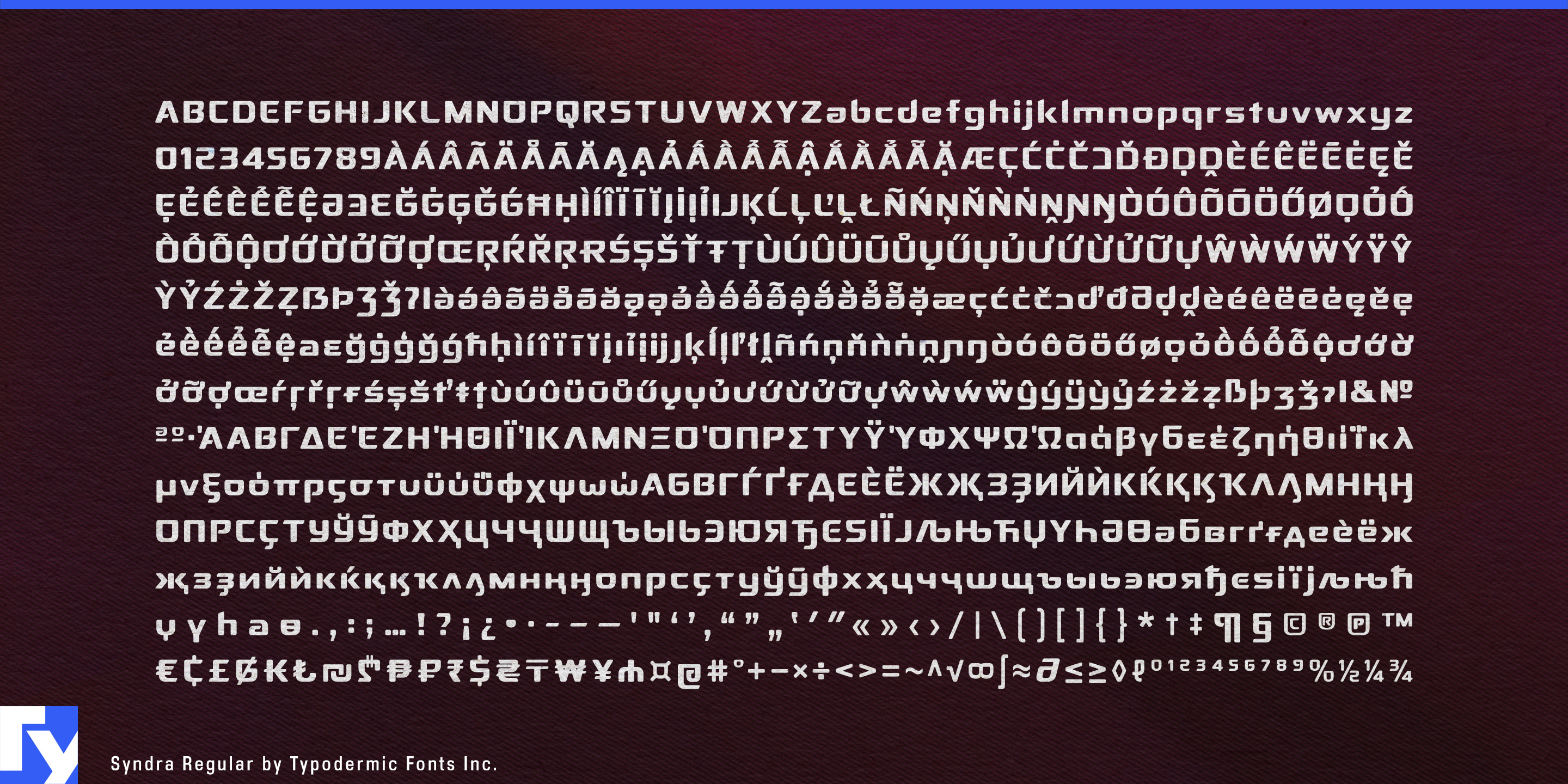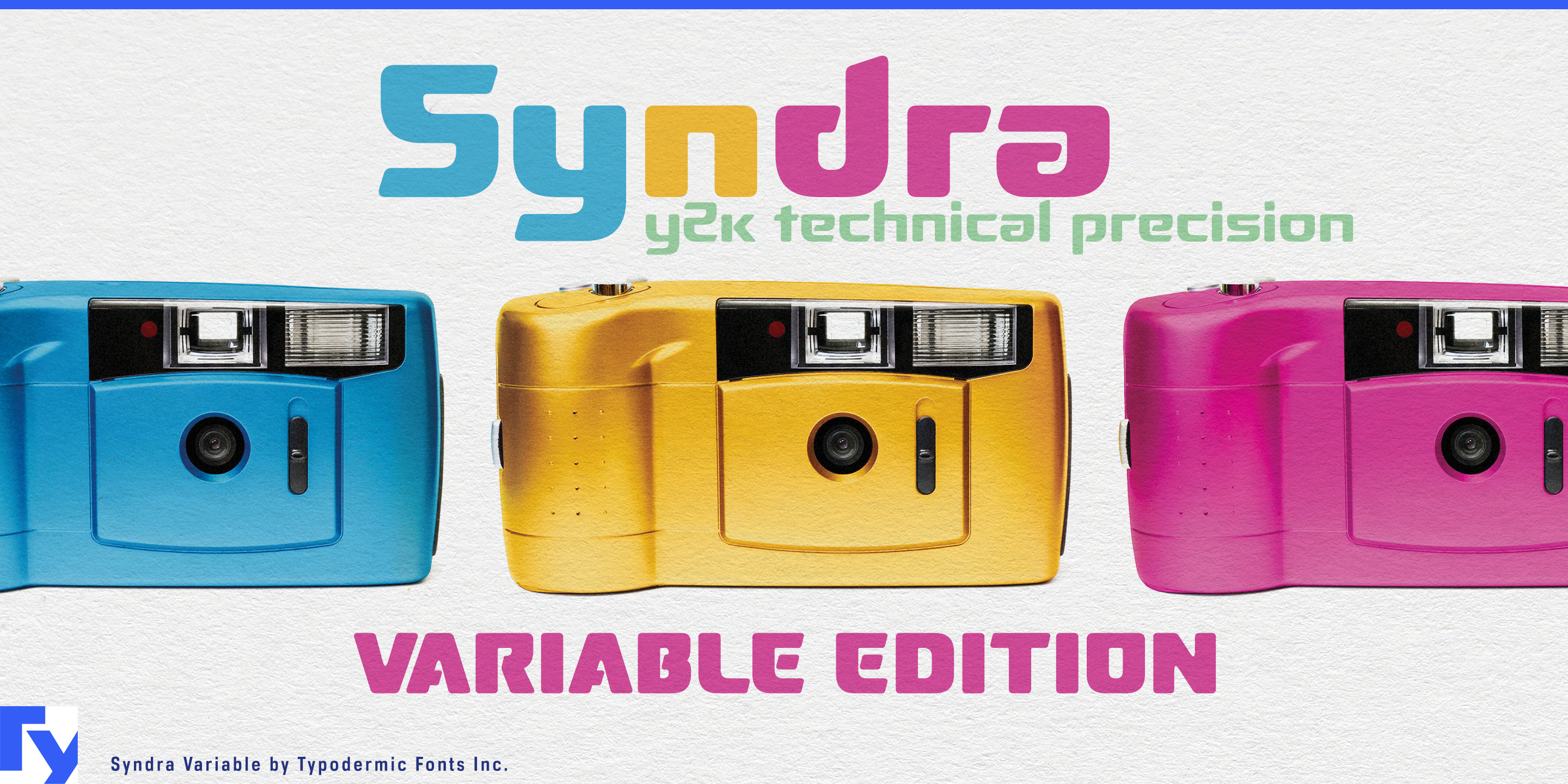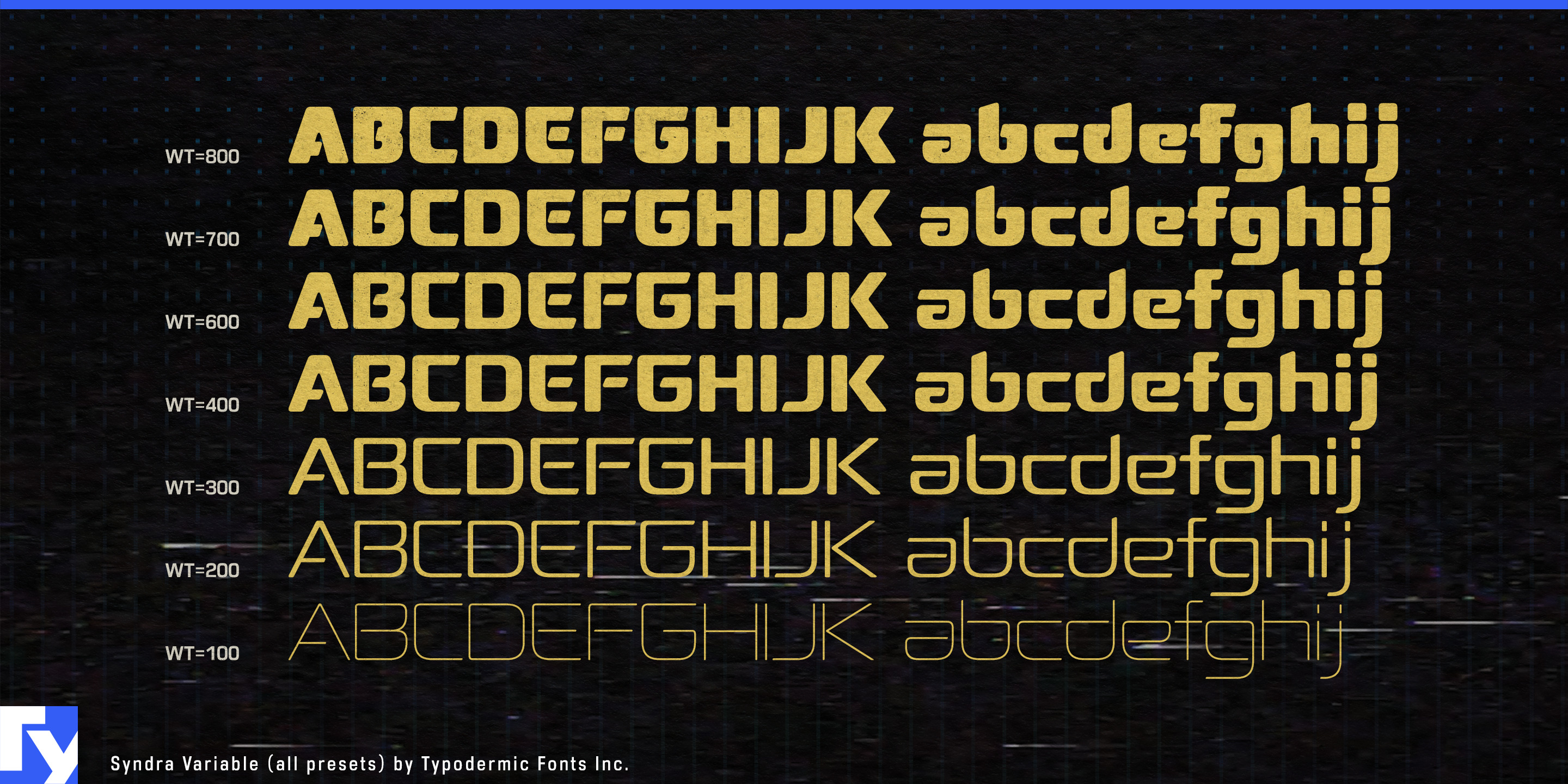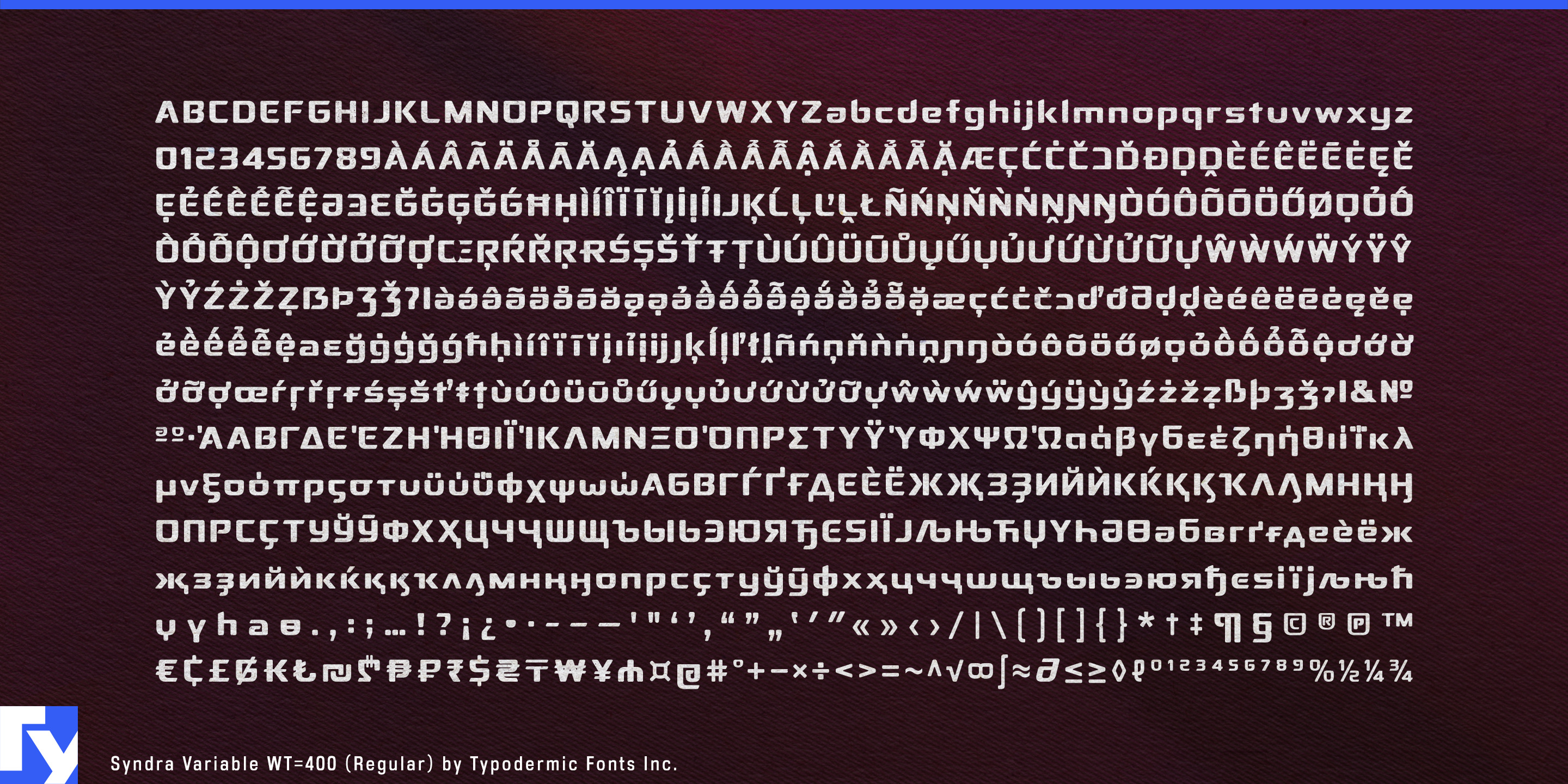
Syndra
技術的に見える書体も、実際の機器に載せるとしっくりこないことがあります。Syndraは文字が製品そのものに置かれるときに力を発揮します。角丸の長方形を基調にした構造、切り詰めた接続部、開いたままのストロークが、成形した筐体、くぼんだ操作部、表示窓など、工業デザインの要素になじみます。
ThinからExtra-Boldまで7つの直立ウェイトで、同じ構造の印象は大きく変わります。軽いスタイルには回路図のような性格があり、太いウェイトは密度が高く、筐体を思わせます。この幅があるため、一つの視覚システムで製品名、モデル名、短いラベル、ディスプレイ文字の情報階層を組めます。
携帯型スピーカー、バッテリーパック、カメラ、レーザー測定器、3Dプリンター、電子計測器では、Syndraの幾何学が実物と結びつきます。EV充電器、家庭用蓄電池、太陽光発電用インバーター、ヒートポンプ、eバイクの電装部品といった新しい家庭向け機器にも合います。機械的な構造が機器上で説得力を持ち、角丸が印象を厳しくしすぎません。
医療、診断、リカバリー用の機器も有効な領域です。理学療法用機器、歯科機器、研究室の計測器、フィットネスマシンでは、ブランド名、製品シリーズ、モデル番号、大きな画面ラベルにSyndraを使い、仕様や長い説明は控えめな併用書体に任せられます。
軽いウェイトは科学館の展示、工業デザインの発表、技術博物館、工学的なグラフィックにも合います。短い見出し、注記、図のラベルを、太いディスプレイタイトルと同じ視覚言語で組めます。Syndraの強みは単に技術的に見えることではありません。設計された製品や技術的な環境に、物自体と一緒にデザインしたような文字を与えます。